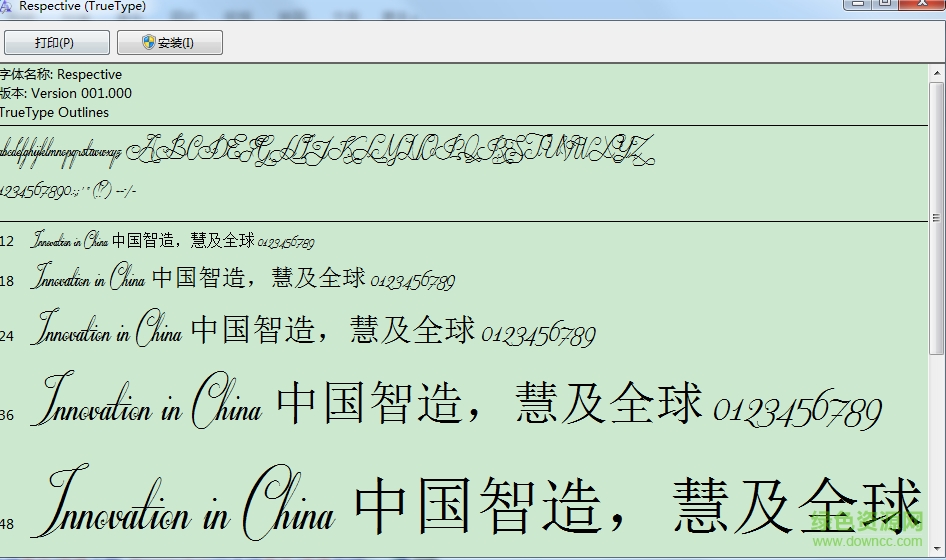
respective字體是一款非常有特色的藝術(shù)字體,這款字體字形優(yōu)美,可以廣泛應(yīng)用于宣傳海報(bào)、ppt、影視制作、廣告設(shè)計(jì)、藝術(shù)設(shè)計(jì)以及任何使用文字的領(lǐng)域,需要的朋友歡迎來(lái)本站免費(fèi)下載使用。